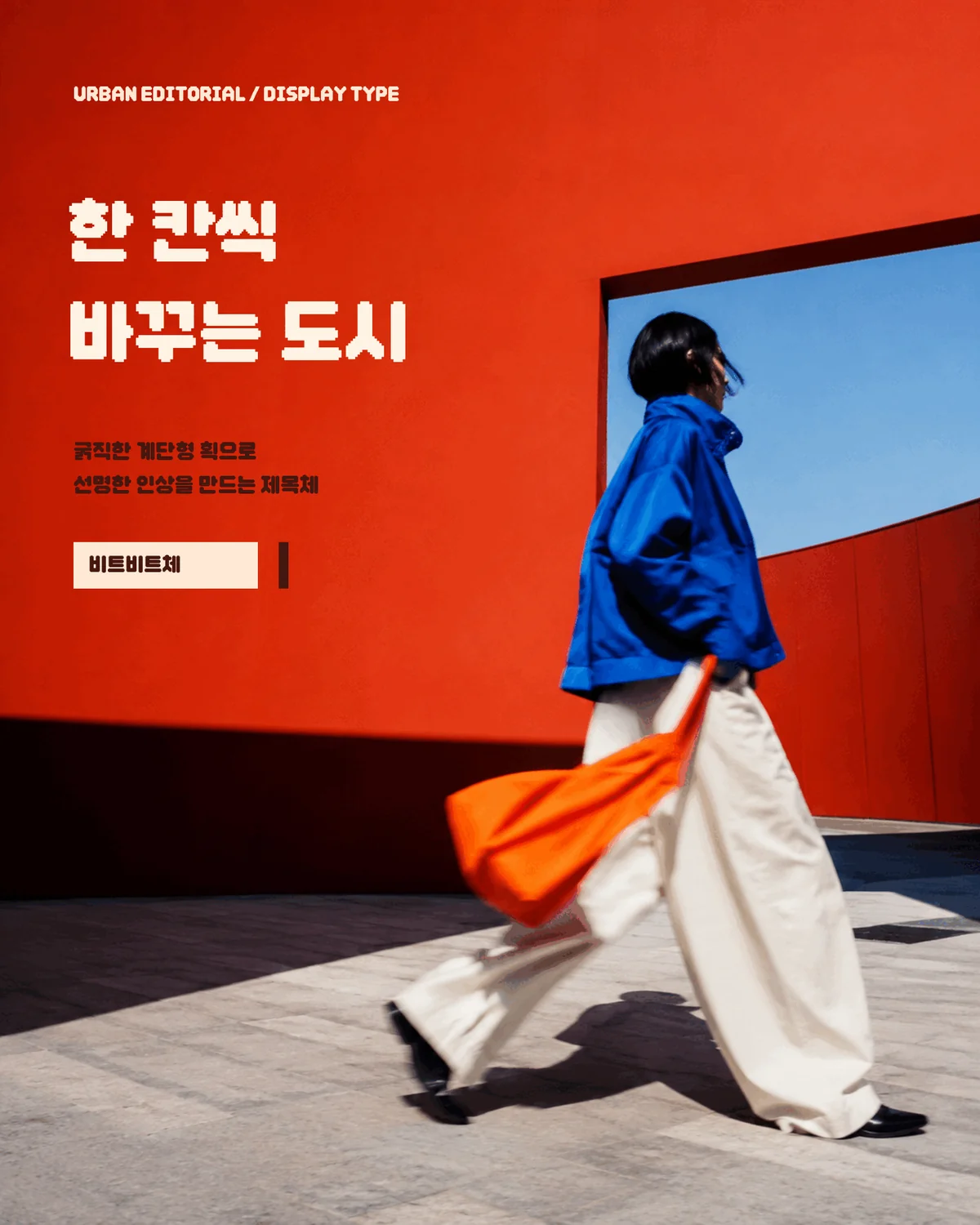
던파 비트비트체 무료폰트
던파 비트비트체 — 넥슨에서 배포하는 무료 폰트입니다. 8비트 게임의 도트 감성을 굵직한 계단 형태로 표현한 픽셀 스타일 제목체
넥슨의 네오플이 던전앤파이터를 위해 2022년에 만든 픽셀 서체입니다. 소개 문구부터 게임답습니다. 폰트도 정성껏 깎았다면서 굵직한 픽셀 느낌이 매력 있는 제목용 서체라고 밝히고, 도트처럼 작으면 작아서 귀엽고 크면 크게 귀엽다고 덧붙입니다.
픽셀 서체라 크기를 고를 때 요령이 있습니다. 픽셀 격자에 맞춰 그린 글자이므로 어중간한 크기로 쓰면 격자가 어긋나 흐릿해집니다. 8이나 16의 배수처럼 딱 떨어지는 크기로 쓰는 편이 또렷합니다.